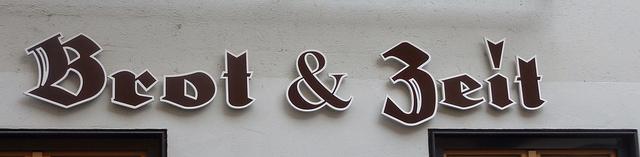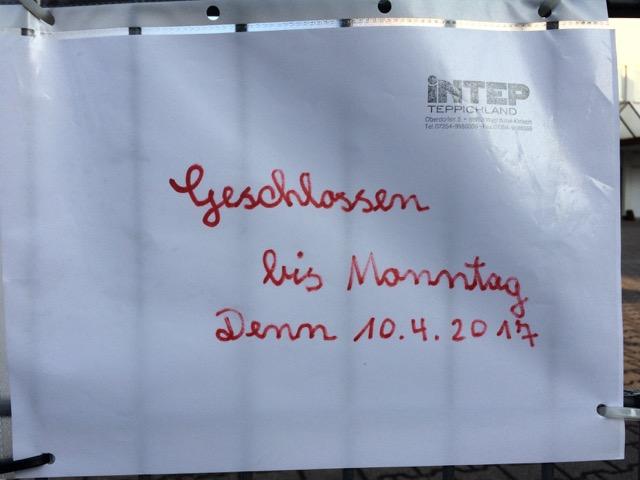
Und ich finde den noch nichtmal schön
Ich finde die Idee an sich ganz nett, aber das Ergebnis ziemlich effektbekifft und in Bezug auf die Formen grob und unausgegoren. Außerdem stören mich die zugekitteten Stellen und die Tropfen.
Ach, und ich dachte, das wäre wenigstens etwas "cooles, hippes" :hammer: - aber du hast recht, ich muss mir unbedingt das Interrobang auf die Tastatur bauen.
It’s a spelling, not a grammar vigilante.
Well done, terminology vigilante! :gimmifive:
:tuschel: But since the vigilante is a person, he’s not an “it.”
The it is an expletive and does not refer to the person. It’s the same it as in this sentence or “it’s him”.
Nö. Es geht hier – anders als z.B. bei “it’s him” – nicht darum, einen Vorfall zu beschreiben (etwa: “What’s that noise?” “Don’t worry, it’s just him; he probably knocked over this toys again.”), sondern es geht explizit um den Apostrophenbeseitiger. Wir kennen ihn schon, wissen, dass er ein Mann ist; er ist das Subjekt, denn sein Status – grammar or spelling nazi – wird debattiert. Es geht nicht darum, ob irgendetwas (“it”) durch einen spelling nazi oder eine andere Person, einen grammar nazi, verursacht wurde, sondern welche Art von nazi dieser konkrete Mensch ist.
Der von dir verlinkte Artikel beschreibt einen einfachen Test, um den Unterschied heraus zu finden:
[A Dummy pronoun] cannot be replaced by any noun phrase
Man kann aber problemlos sagen: The sticker-weilding Bristol man is a spelling, not a grammar vigilante.
Davon abgesehen ist das Banner natürlich sehr gelungen und man hat praktisch nix daran auszusetzen :hammer::-P
Gehen wir zum Wochenstart heute alle mal mit 'nem Arm voll Steine ins Glashaus?
Vermutlich hatten sie Angst, dass das passende Et keiner lesen kann ...
Bei manchen Frakturen wär's verständlich ...
Der Fairness halber muss man sagen, dass viele Frakturschriften schlichtweg kein passendes Ampersand haben.
... oder sogar gar keines.
Ich mal schnell "Fraktur mon Amour" durch die Finger laufen lassen. Es gibt einige Schnitte, die ein passendes Ampersand haben.